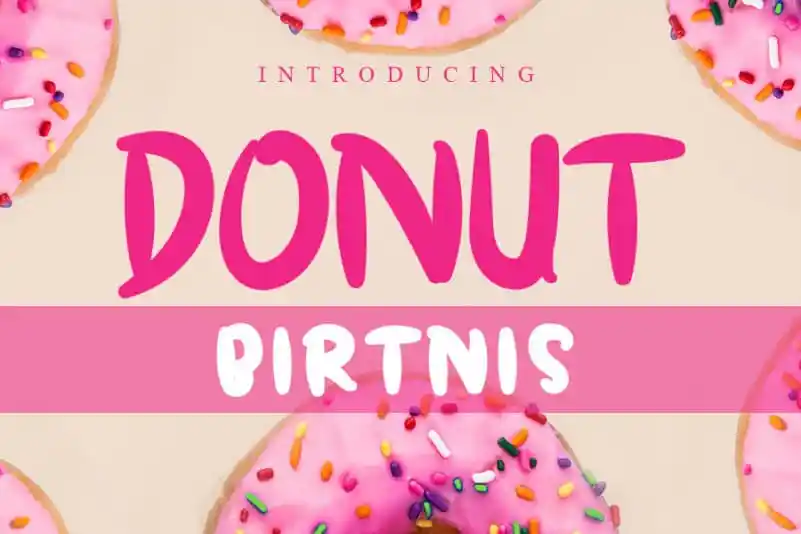
DONUT BIRTNIS Display Font – Download Grátis
A DONUT BIRTNIS Display Font é uma elegante escolha para aqueles que buscam uma mistura única entre a caligrafia clássica e uma aparência contemporânea. Inspirada nas cores vibrantes e na textura do donut, essa fonte transmite atemporais características chamativas. Ela traz um toque revigorante ao texto, mantendo-se moderna enquanto também se destacando. Sua versatilidade torna-a ideal para uma ampla gama de ideias criativas, desde o design do topo da página até os elementos estilizados e as notas de papel. É perfeitamente adaptável a qualquer projeto que exige um toque inovador e chamativo. Seja para criar uma identidade visual memorável ou transformar mensagens em algo excepcionalmente único, esta fonte é certamente uma ótima escolha.